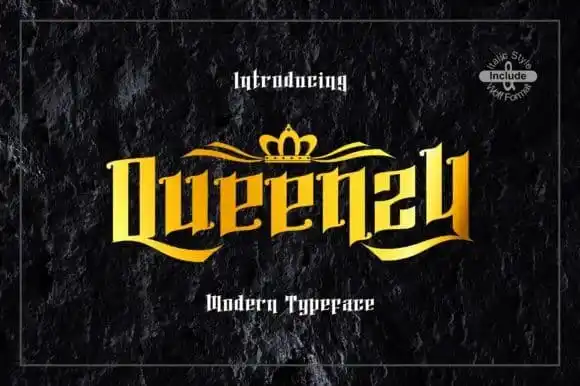
Queenzy Blackletter Font – Download Grátis
A fonte Queenzy Blackletter Font é uma criação sofisticada inspirada no design vintage de postais antigos, cuidadosamente desenvolvida pelo designer Hamilton. Inspirado nas texturas únicas e na sensação real do trabalho artesanal, a fonte traz um toque único e autêntico à sua identidade visual. Ideal para projetos que desejam uma atmosfera nostálgica, ela é perfeita para aplicar em cartazes, revistas de arte ou qualquer outra mídia onde você quer destacar o seu estilo único. Com acesso fácil a todos os gráficos e swashes através da codificação PUA, Queenzy Blackletter Font se torna uma ferramenta versátil e criativa para designers exigentes que buscam personalidade em seus projetos.